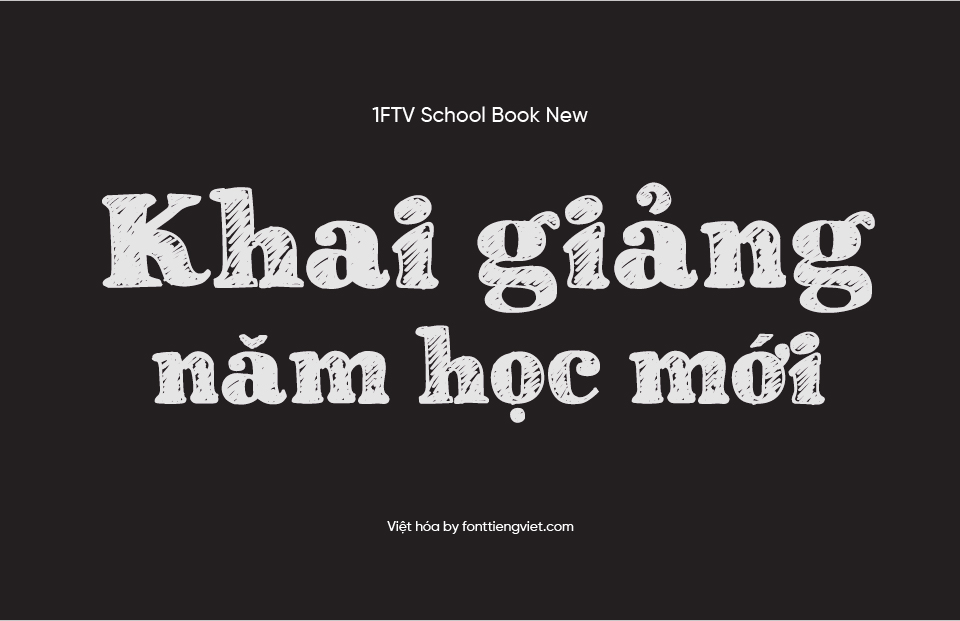
Font Việt hóa 1FTV School Book New – Phấn
Giới thiệu về Font Việt hóa 1FTV School Book New – Phấn
Trong môi trường giáo dục hiện đại, việc lựa chọn bộ Font Miễn Phí phù hợp đóng vai trò quan trọng trong việc truyền tải kiến thức. Font Việt hóa 1FTV School Book New – Phấn là một sản phẩm thiết kế đặc thù dành riêng cho học sinh và giáo viên tiểu học. Với những đường nét mô phỏng nét phấn viết bảng thân thuộc, bộ font này mang lại cảm giác gần gũi và trực quan sinh động. Việc sử dụng font chữ này không chỉ giúp bài giảng trở nên hấp dẫn hơn mà còn hỗ trợ các em học sinh dễ dàng làm quen với mặt chữ chuẩn trong sách giáo khoa.
Đặc điểm nổi bật của Font Việt hóa 1FTV School Book New – Phấn
Thiết kế mô phỏng nét phấn tinh tế
Font Việt hóa 1FTV School Book New – Phấn được chăm chút kỹ lưỡng để tái hiện độ nhám và độ đậm nhạt của phấn trên bảng đen. Các ký tự được điều chỉnh tỉ lệ chuẩn xác, giúp người xem không bị mỏi mắt khi theo dõi nội dung dài. Đây là lựa chọn lý tưởng cho các bài trình chiếu PowerPoint hoặc tài liệu in ấn bổ trợ học tập.
Tương thích hoàn hảo với tiếng Việt
Một ưu điểm lớn của Font Việt hóa 1FTV School Book New – Phấn chính là sự đầy đủ về bảng mã tiếng Việt. Các dấu thanh được đặt đúng vị trí, không xảy ra tình trạng lỗi ký tự hay lệch dòng. Sự đồng nhất này giúp các thầy cô giáo tiết kiệm thời gian chỉnh sửa văn bản, tập trung tối đa vào việc sáng tạo nội dung giảng dạy chất lượng cao.
Ứng dụng thực tiễn trong giảng dạy
Bộ Font Việt hóa 1FTV School Book New – Phấn cực kỳ đa năng khi áp dụng vào thực tế. Từ việc thiết kế nhãn vở, thời khóa biểu cho đến làm tiêu đề các trang giáo án điện tử, mọi thứ đều trở nên chuyên nghiệp và giàu tính thẩm mỹ. Kết luận, nếu bạn đang tìm kiếm một công cụ hỗ trợ trình bày đẹp mắt, hãy tải ngay tại Font Miễn Phí, Font Việt Hóa, Font Việt hóa 1FTV School Book New – Phấn để trải nghiệm sự khác biệt trong từng nét chữ.